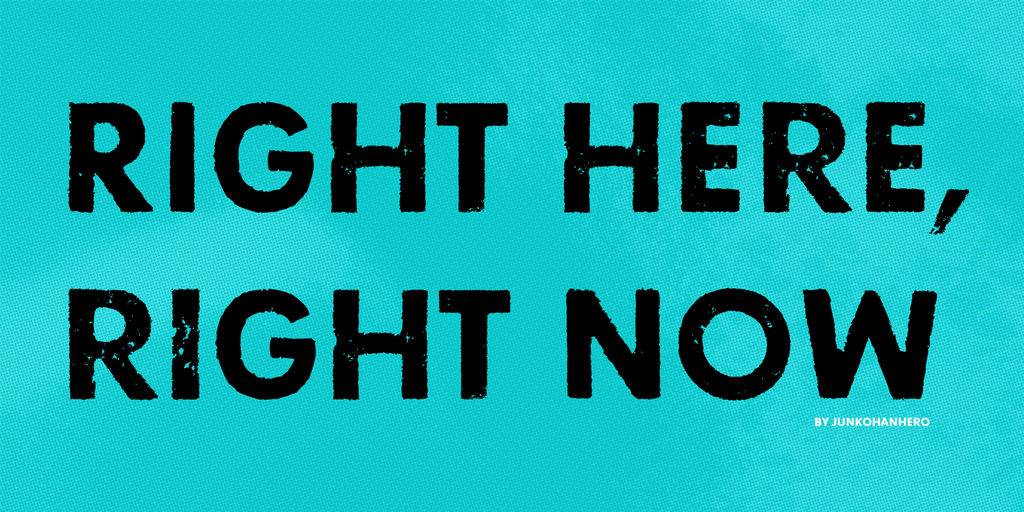
A fonte Right Here, Right Now é uma opção ideal para criar designs modernos e dinâmicos. Desenhada pelo designer Hamilton, essa fonte destaca-se pela sua característica clean e elegante que se adapta perfeitamente a diversos estilos de design, desde o minimalista até ao sofisticado. O download gratuito da font garante um uso pessoal, mas para usos comerciais mais avançados, é necessário adquirir uma licença comercial. Para isso, você pode comprar por 15 euros em Euros (€) ou $20 em dólares através do PayPal. Após a conclusão do pagamento, envie-nos um e-mail para confirmar o processo. Além disso, temos um botão de doação próximo ao botão de download, garantindo que o acesso à fonte seja fácil e conveniente. Tornando-se dono desta font, você pode explorar todas as suas possibilidades em projetos comerciais, desde designs de logotipos até materiais impressos. Right Here, Right Now é uma escolha inteligente para quem procura uma fonte de qualidade que se adapte às necessidades do seu trabalho, sem comprometer a criatividade ou o design final. Com sua simplicidade e eficiência, esta font está aqui para ajudá-lo a expressar os seus projetos de maneira única e imediatamente apreciável. Não perca tempo, baixe já a sua cópia e comece a criar!